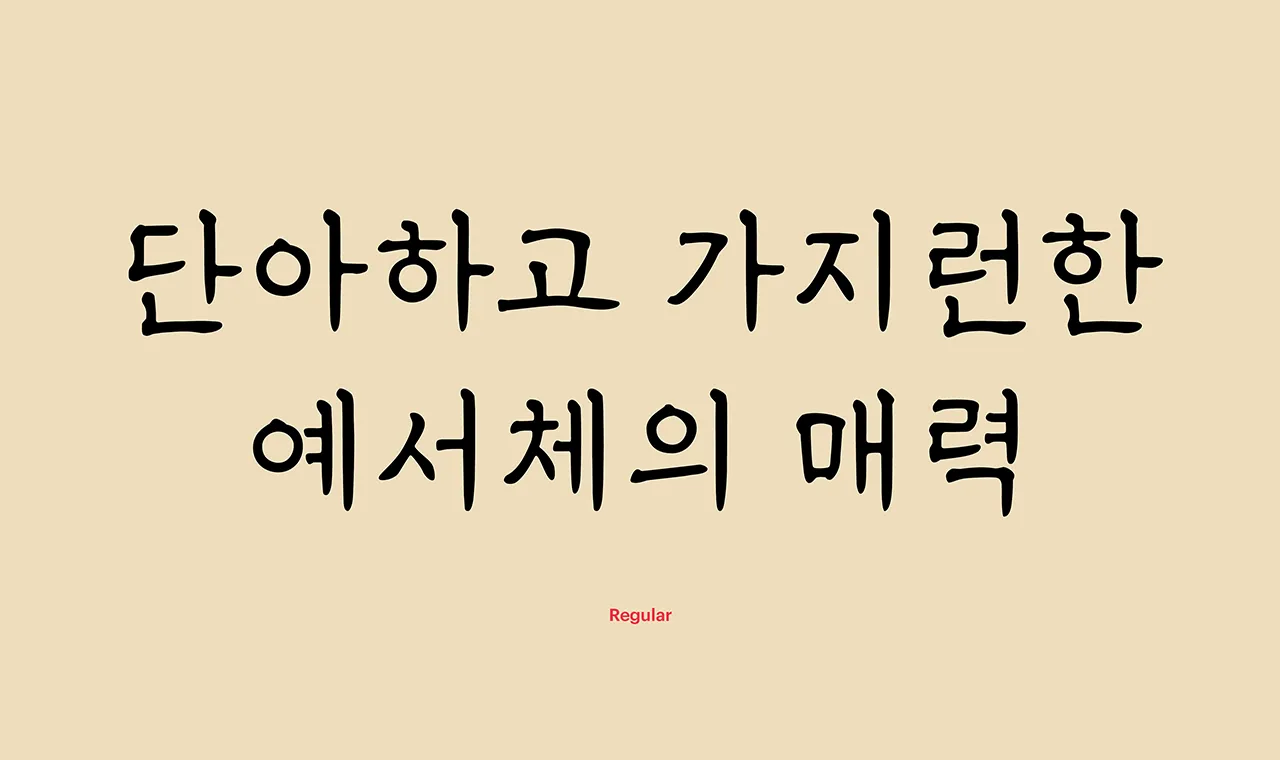
사진 식자 시대의 해서체와 예서체 원도를 디지털 폰트로 완성, 누구나 우리 글자의 아름다움을 체험할 수 있도록 한 윤디자인×이천섭 아티스트 폰트 콜렉션
소하 이천섭은 붓글씨를 사용한 최초의 폰트 소하체 원도의 주인공입니다. 서예 글씨를 폰트로 만든다는 개념 자체가 낯설던 시절, 그의 시도가 있었기에 우리는 우리 전통 서예의 아름다움을 가까이에 두고 되새길 수 있게 되었죠. 곧은붓, 어진붓으로 구성된 소하 이천섭 아티스트 폰트 콜렉션 의의 역시 전통의 일상화에 있습니다. 소하 이천섭이 6년여에 걸쳐 작업한 사진 식자 시대의 해서체와 예서체 원도를 디지털 폰트로 완성함으로써 누구나 우리 글자의 아름다움을 손쉽게 체험할 수 있게 된 것입니다.
유려미 곧은붓, 단정미 어진붓
해서체의 아름다움을 머금은 곧은붓은 날카로운 획의 시작과 도톰한 끝이 우아한 곡선미를 완성해내는 폰트입니다. 획과 획이 연결되는 부분에는 붓글씨 특유의 흘림이 남아 있어 해서체만의 유려한 개성을 전달하지요. 반면 예서체의 단정한 멋을 잘 표현한 어진붓은 사각형 틀에 가지런히 들어가는 구조를 지니고 있습니다. 획의 방향이 간결하게 수직/수평을 이루고 획의 시작과 끝, 꺾임 부분은 부드럽게 처리되어 예서체만의 정갈하고 단단한 표정을 보여줍니다.
전통미를 일상화하는 폰트 콜렉션
이처럼 해서체와 예서체의 전통미를 디지털 폰트로 구현해낸 이천섭 아티스트 폰트 콜렉션은 한글, 한자, 숫자, 영문의 디자인적 통일성까지 확보해 어떤 환경에서도 어려움 없이 사용할 수 있도록 신경 썼습니다. 오래되고 근본적인 아름다움을 나의 일상 가까이에 배치하고 싶다면 지금 바로, 이천섭 아티스트 폰트 콜렉션과 조우해보시죠.
곧은붓Regular
사진 식자 시대의 해서체 원도를 기반으로 완성한 유려한 폰트입니다. 획마다 살아있는 곡선미와 흘림의 우아한 아름다움을 만끽할 수 있습니다.
어진붓 Regular
사진 식자 시대의 예서체 원도를 기반으로 완성한 단정한 폰트입니다. 반듯한 획과 사각의 구조가 한글의 기하학적 조형미를 보여줍니다.